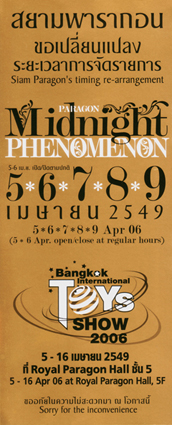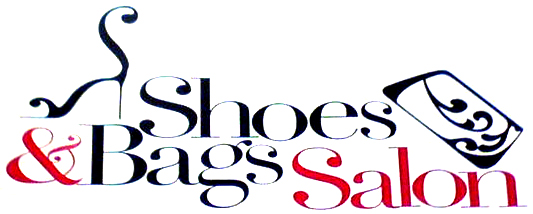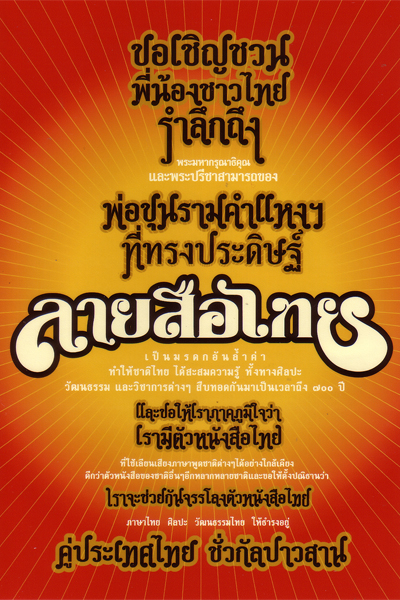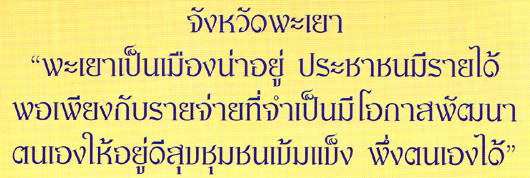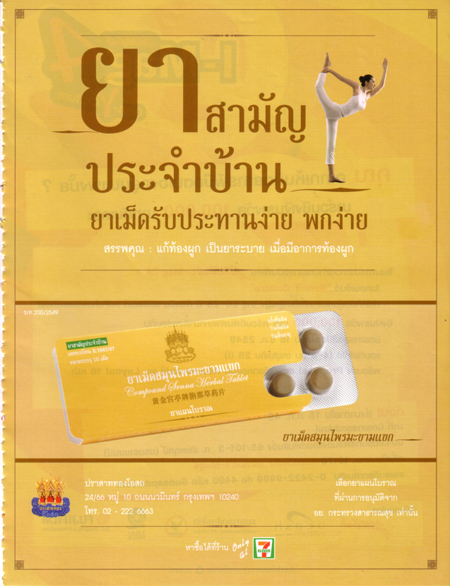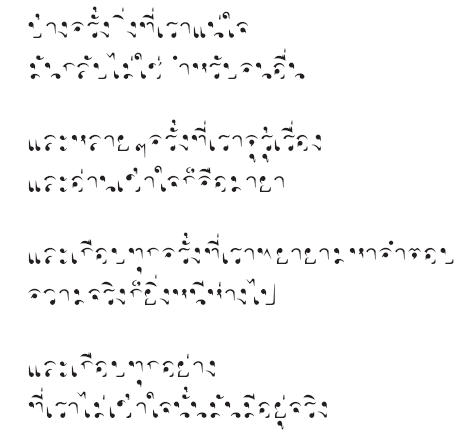
Type Gallery
เอาฟอนต์หรือ Type สวยๆ / แปลกตา ที่เจอจากที่ต่างๆมาโชว์ตัวกัน
(ยังคงไม่แน่ใจว่าใช้คำไหนถึงจะถูก แม้จะรู้ความหมายอยู่บ้างก็ตาม)
โดยเฉพาะที่เป็นอักษรไทยก็ยิ่งเยี่ยมเลย
ประเดิมด้วย
จากสยามพารากอน เป็นที่ชื่นชมจากกลุ่มอาจารย์ใน Typothai ด้วยนะ
ชอบรองเท้าตัว S นั่นจัง
ยังไม่รู้ชื่อฟอนต์ และผู้ออกแบบ
ไปลองถามๆดู ไม่รู้ว่าของ JWT รึเปล่า
Postcard 1 ใน Thesis จาก นิทรรศการ +    14VOLTS    -
นิเทศศิลป์ มหาวิทยาลัยกรุงเทพ เพิ่งไปดูมาวันนี้เอง
อาจจะเป็นลูกศิษย์อาจารย์โรจหรืออาจารย์เอกก็ได้
คิดว่าเอา PSL ThaiCommon มาเพิ่มความมันส์
จริงๆงานเค้าเป็น Animation แบบประโยคภาษาไทยหมุนไปหมุนมา
Postcard สวยดี แต่ดูคล้าย Poster ของตื่นเถิดกราฟิกไทย
ฟอนต์นี้ก็สวย ชอบมาก แต่ไม่รู้ว่าชื่ออะไร ใครรู่ตอบด้วย
เป็นหน้าโฆษณาในนิตยสาร เห็นว่ามันแปลกดี
เพราะปกติหน้าโฆษณาจะเน้นรูปให้เห็นตัวสินค้าใหญ่ๆหรือเห็นนางแบบชัดๆ ข้อความจะเล็กๆเป็นส่วนประกอบ
แต่อันนี้กลับกัน type ใหญ่เด่นเด้ง แล้วคุมโทนสีซะเนียนเชียว ก็เลยดูแปลกตา
หาจากแถวนี้มาแปะ
สวยมากเลยนะ สวยจริงๆ